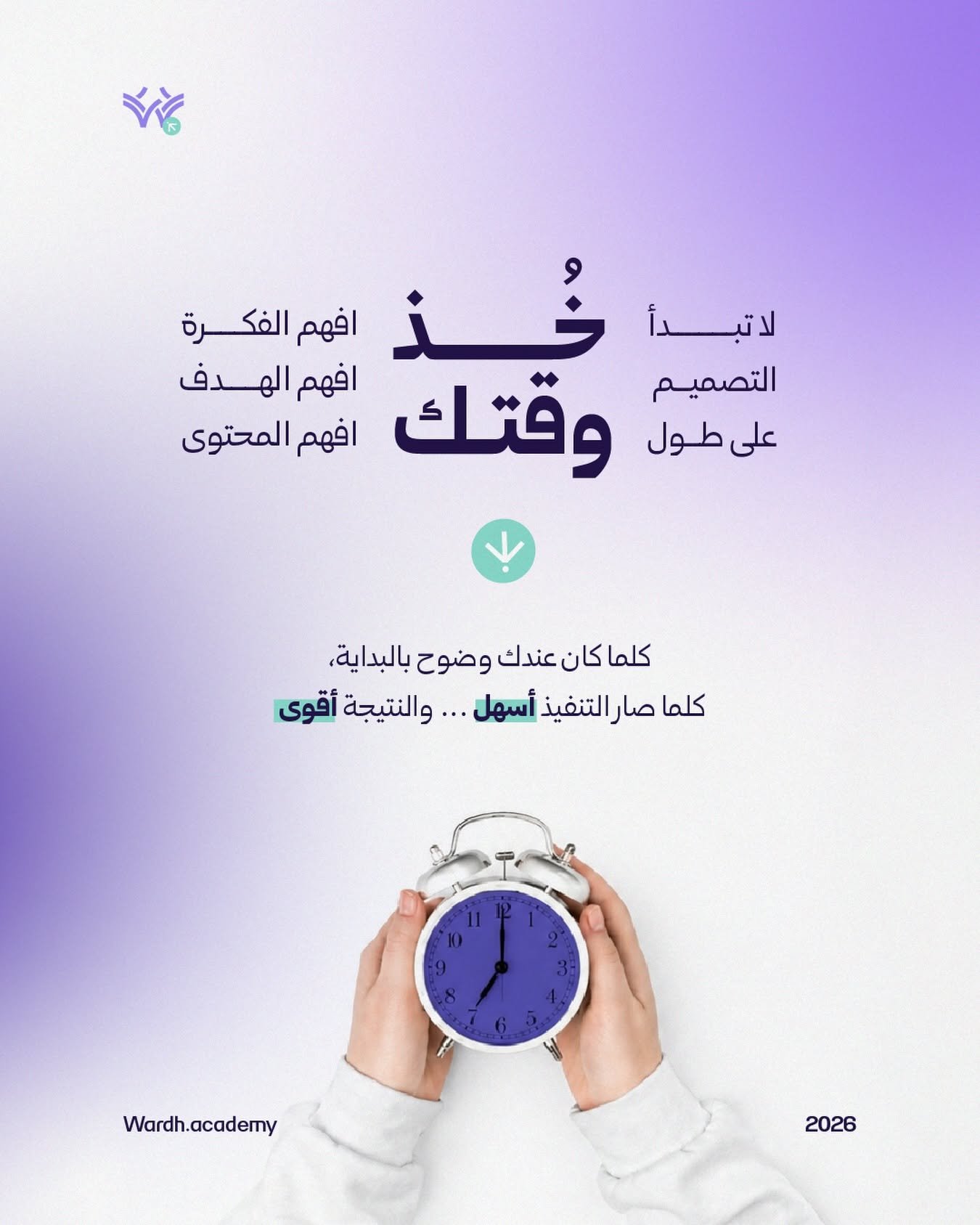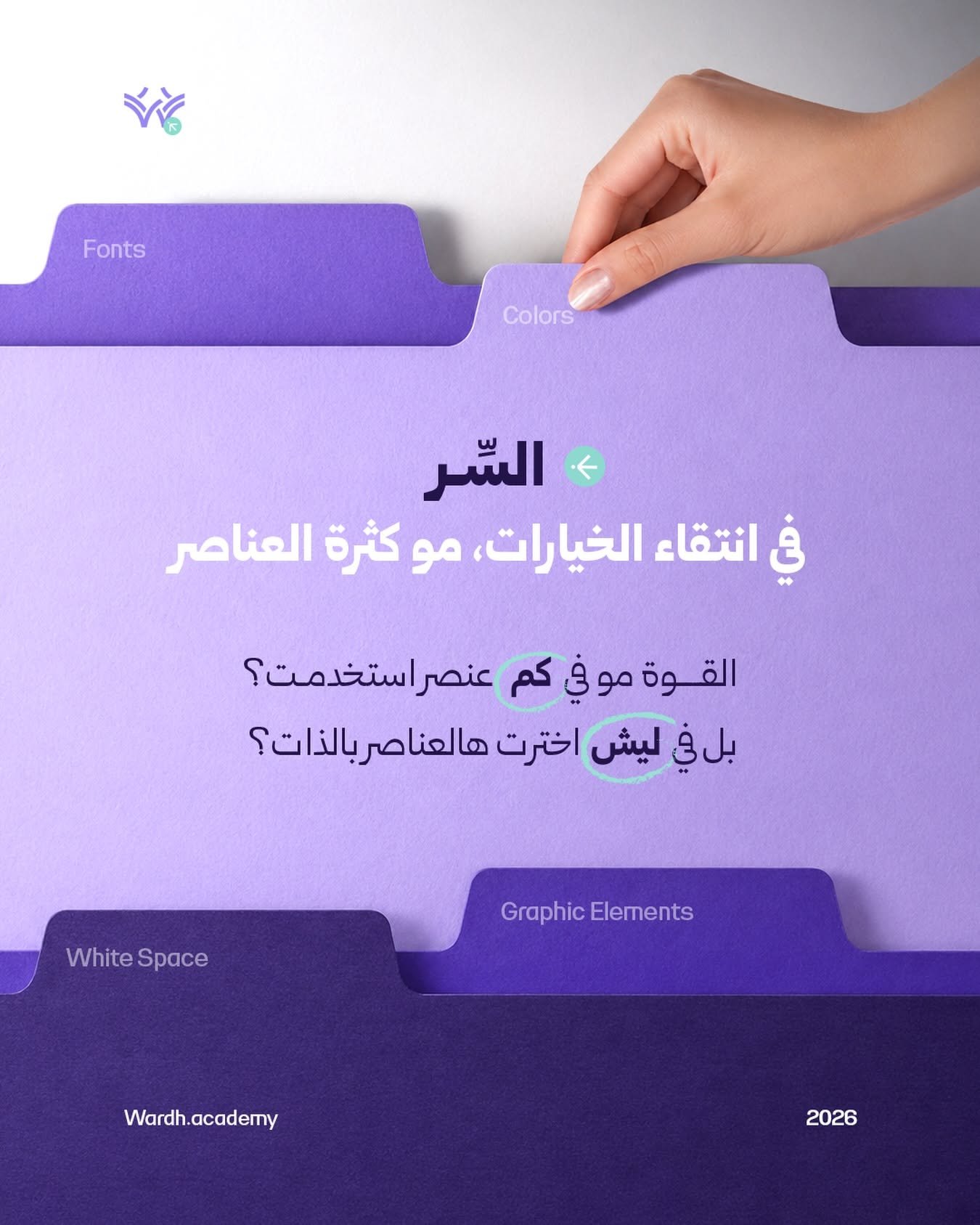
خط غروب نستعليق في أعمال وردة أكاديمي — خط نستعليق عربي
وردة أكاديمي
هو إصدار مشتق من عائلة خط غروب، يقدّم معالجة معاصرة تجمع بين بنية النسخ وروح النستعليق، مع توجّه هندسي واضح وتبسيط بصري يمنح الخط شخصية هادئة، متزنة، وسهلة الاستخدام في مختلف السياقات التصميمية.